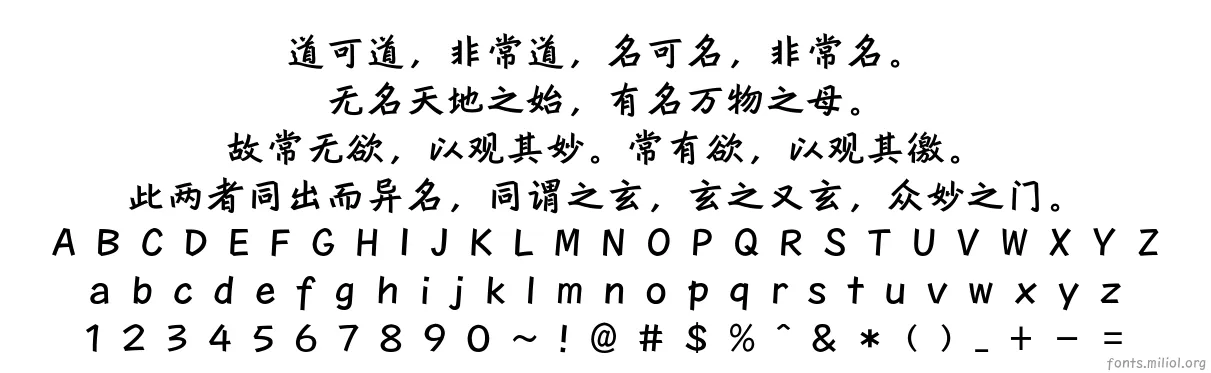
**方正行黑简体字体简介**
方正行黑简体(FZXingHeiS-R-GB)是一款由方正字库设计的中文黑体字体,兼具现代感与实用性。其笔画简洁有力,结构匀称,适用于标题、广告、品牌宣传等多种设计场景。字体风格稳重而不失灵动,既适合印刷品,也适配数字屏幕显示,具有良好的可读性。
作为GB2312编码的标准字体,方正行黑简体支持简体中文常用字符,满足日常设计需求。其文件名标注为FZXHJW--GB1-0,属于方正字库的经典系列之一。设计师可凭借其清晰的线条和均衡的布局,提升视觉传达效果。